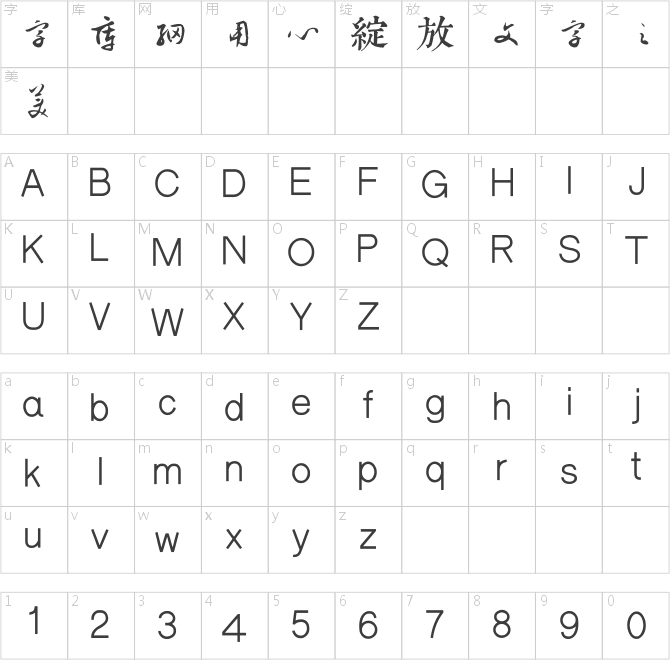
邯鄲文征明千字文
邯鄲文征明千字文介紹
邯鄲文征明千字文字體下載邯鄲(明)文征明千字文
文徵明(1470年11月28日-1559年3月28日),原名壁(或作璧),字徵明,四十二歲起,以字行,更字徵仲。因先世為衡山人,故號衡山居士,世稱“文衡山”。南直隸蘇州府長洲縣(今江蘇蘇州)人。明代畫家、書法家、文學家、鑒藏家。
文徵明曾學文于吳寬,學書法于李應禎,學畫于沈周,生平九次參加鄉試均不中。嘉靖二年(1523年),以歲貢生參加吏部考試,被授予翰林院待詔之職。嘉靖五年(1526年),文徵明辭官歸鄉,專事創作。
嘉靖三十八年(1559年)二月二十,文徵明去世,享年九十。其弟子私謚貞獻。
文徵明詩、文、書、畫無一不精,人稱“四絕”,其與沈周共創“吳派”。在畫史上與沈周、唐寅、仇英合稱“明四家”。在文學上,與祝允明、唐寅、徐禎卿并稱“吳中四才子”。